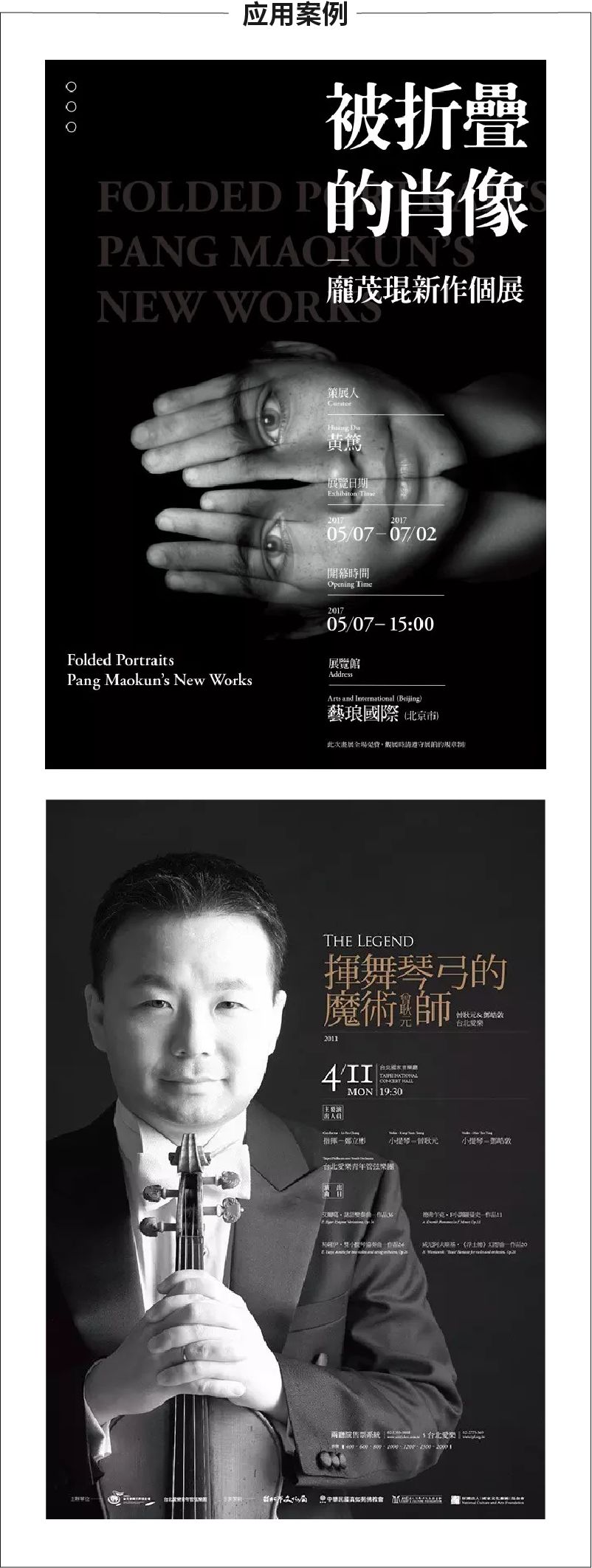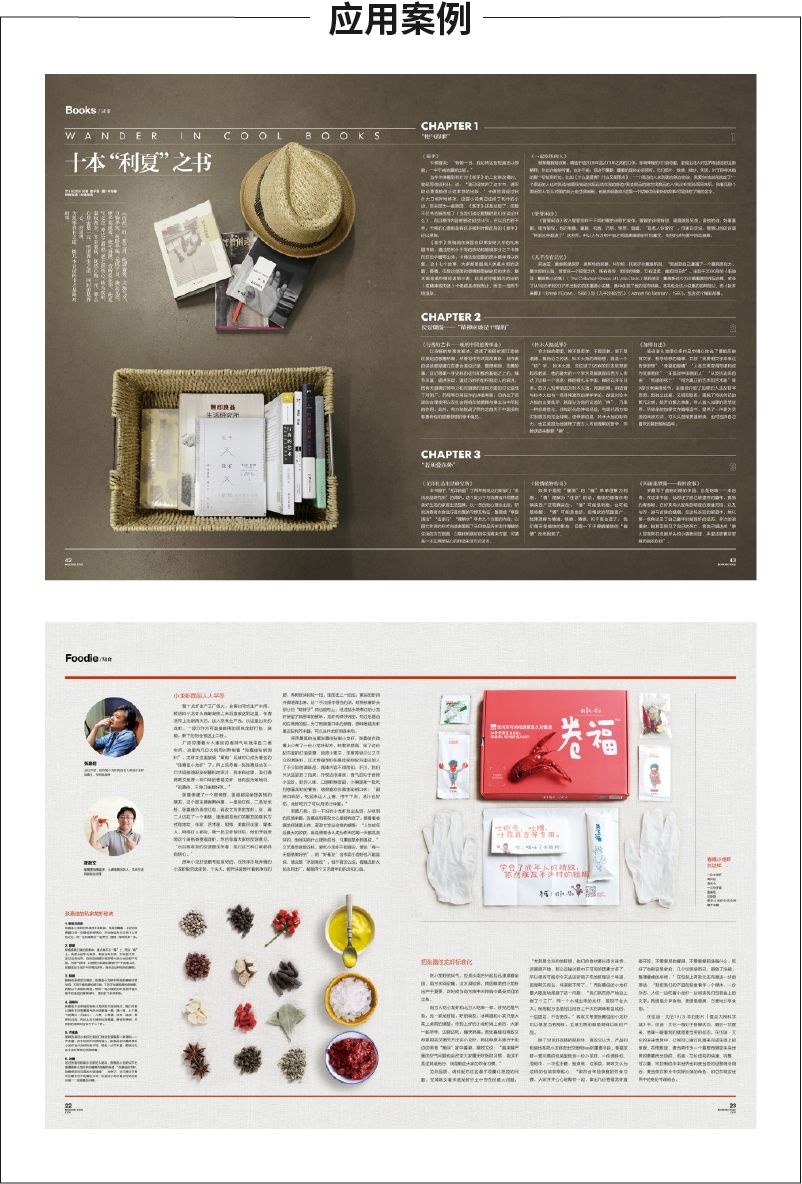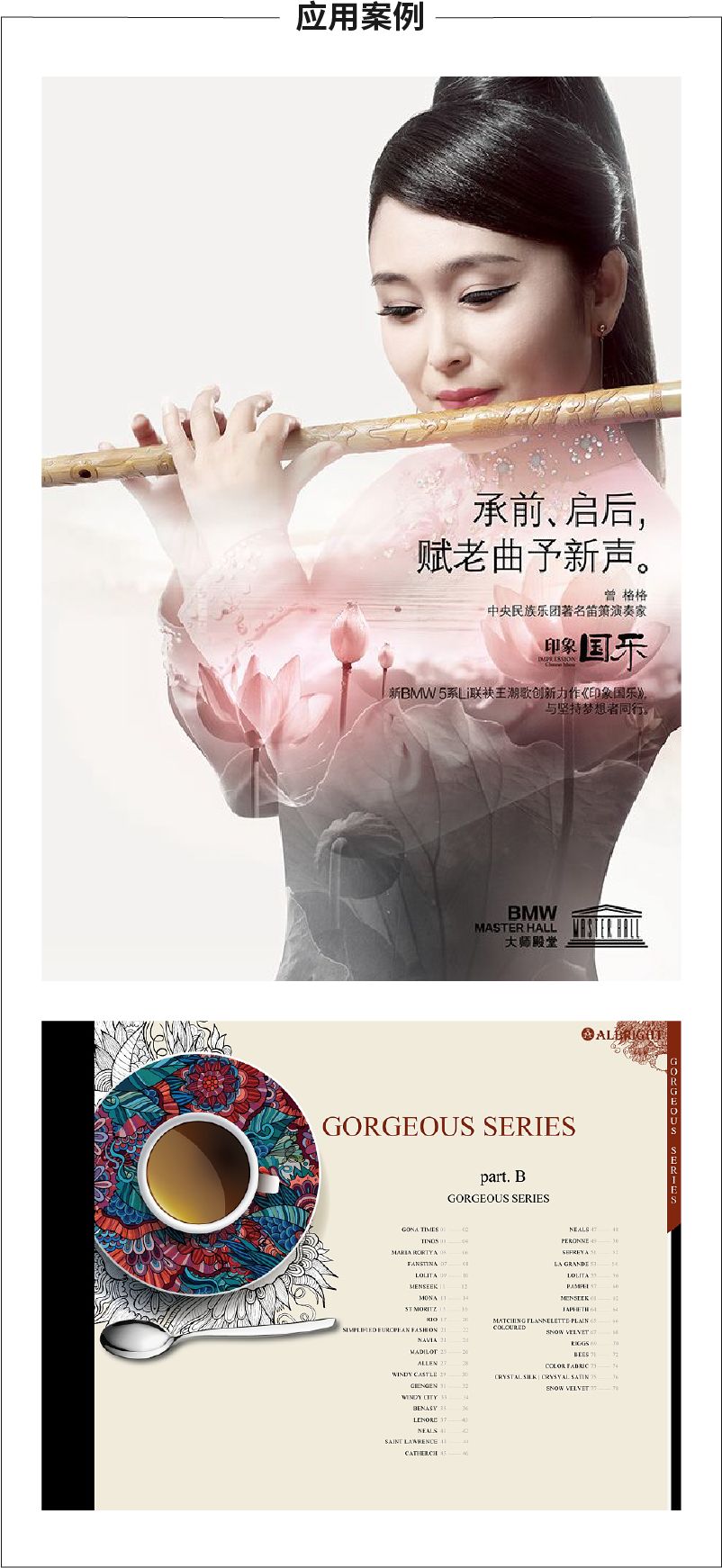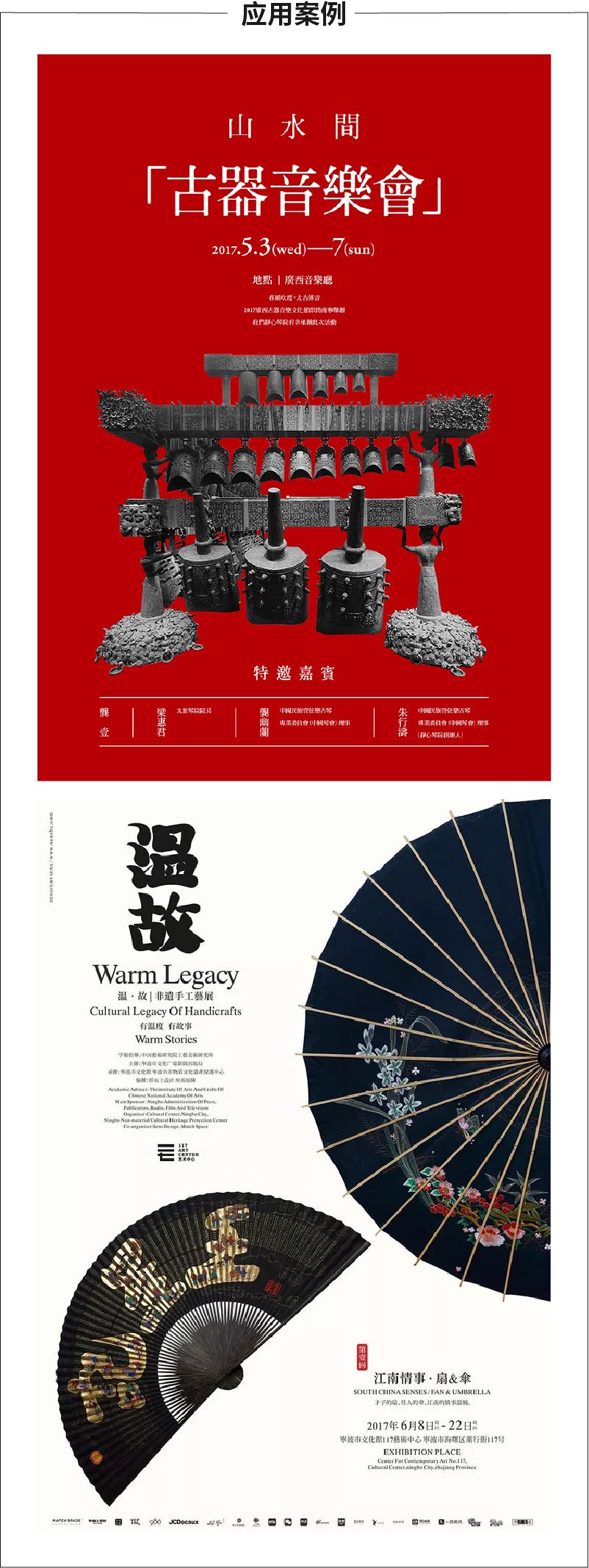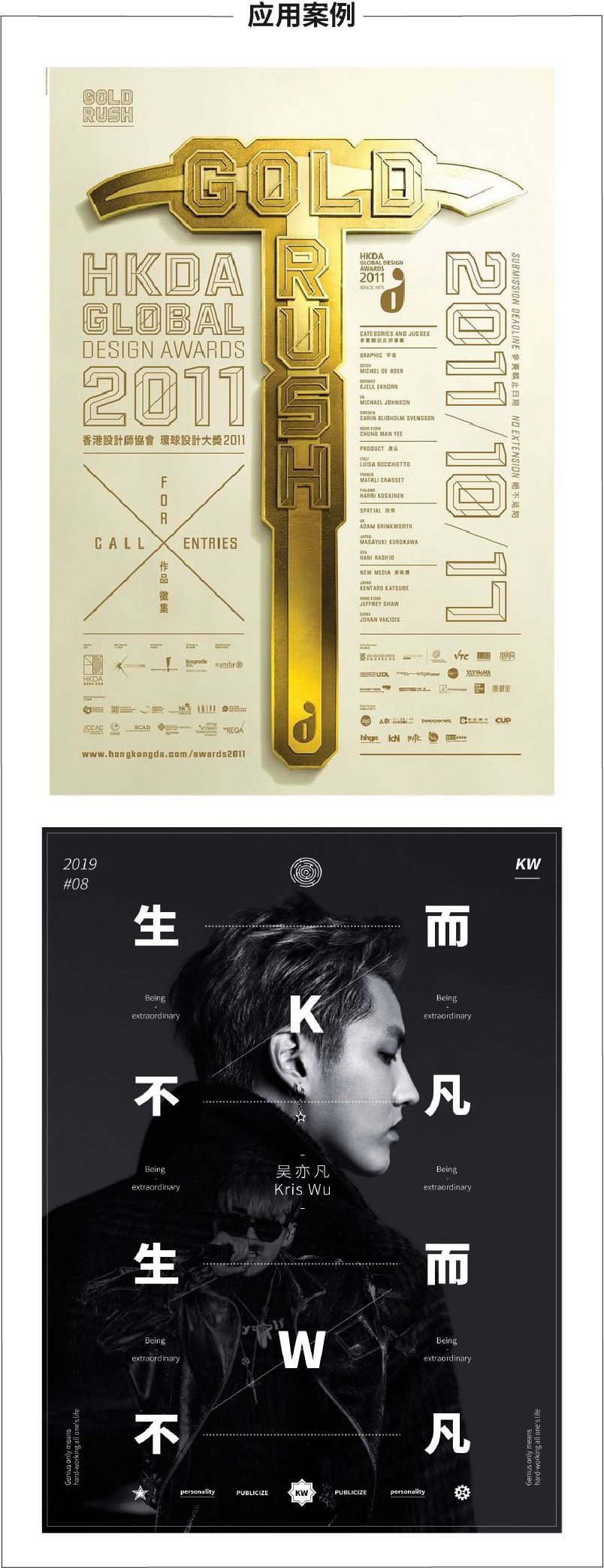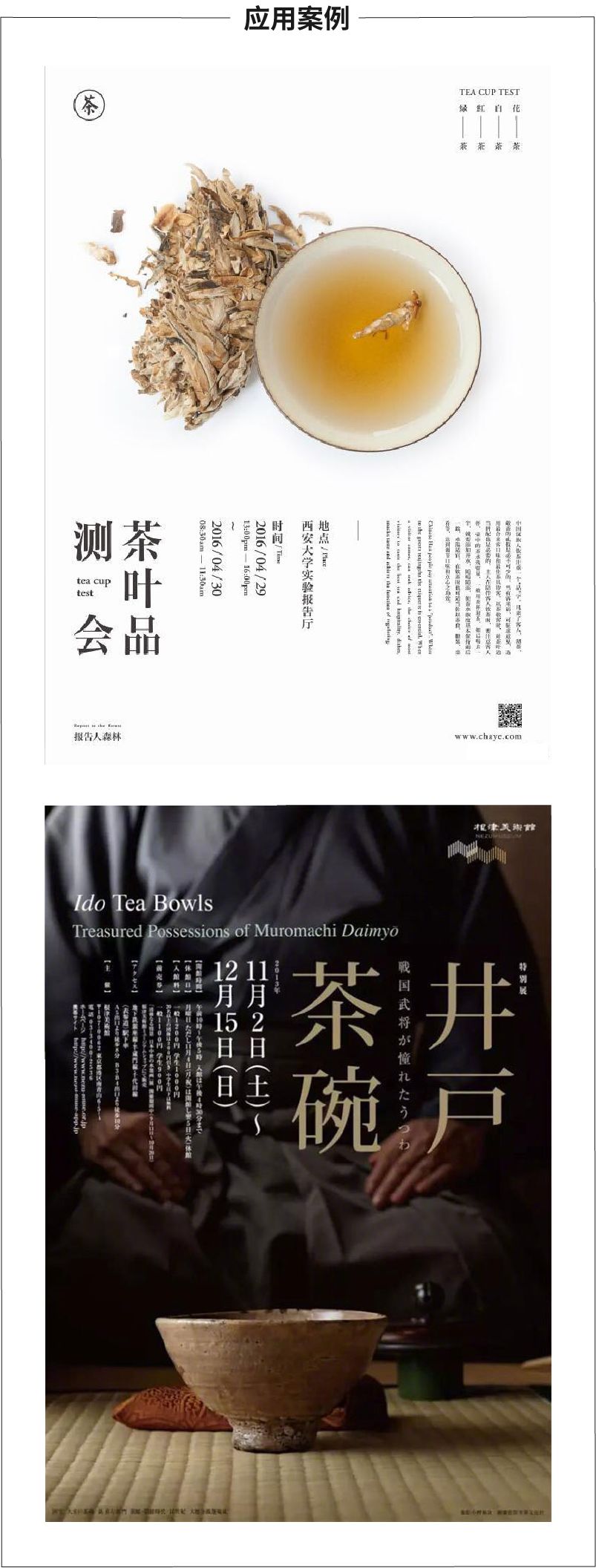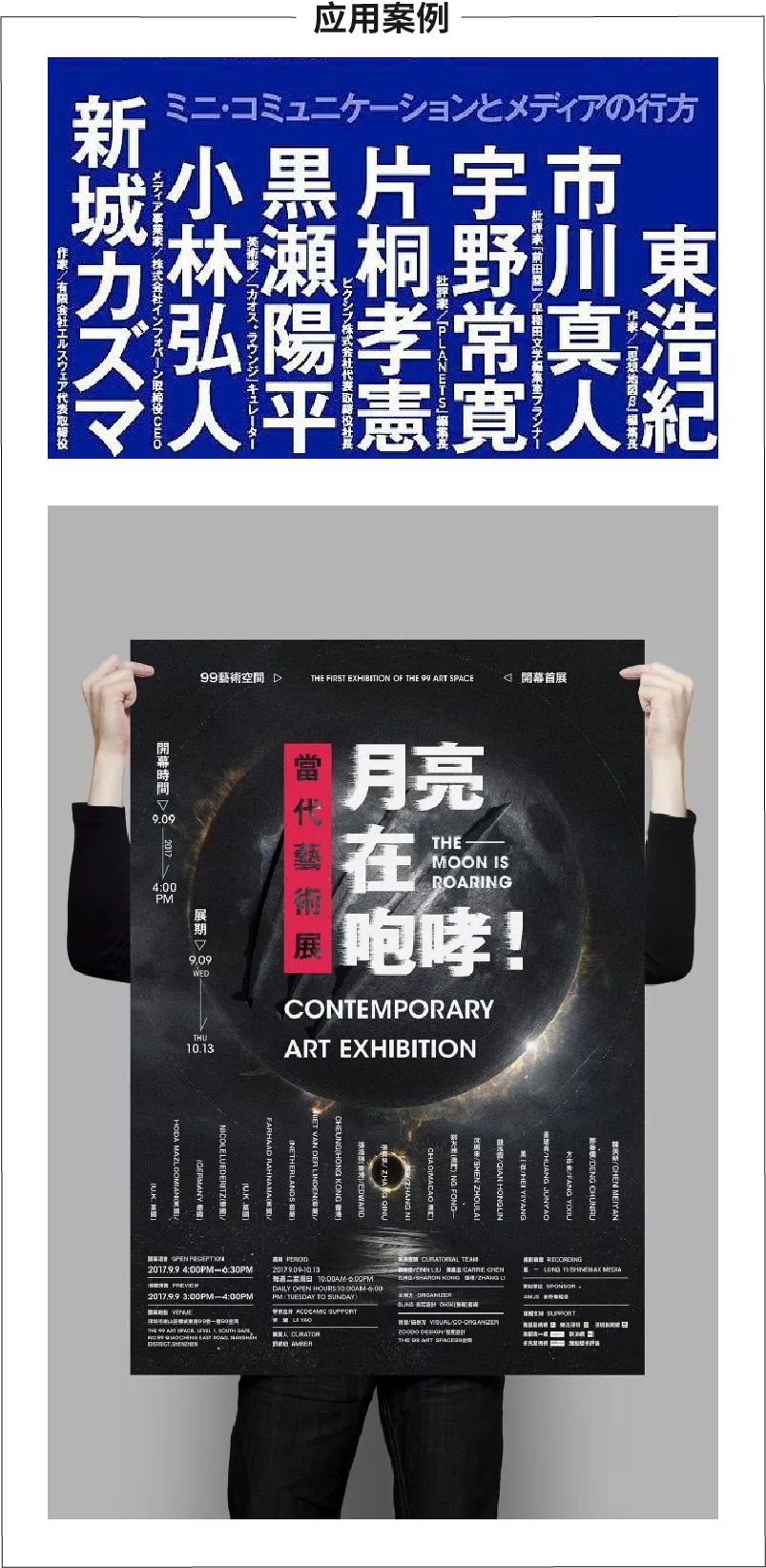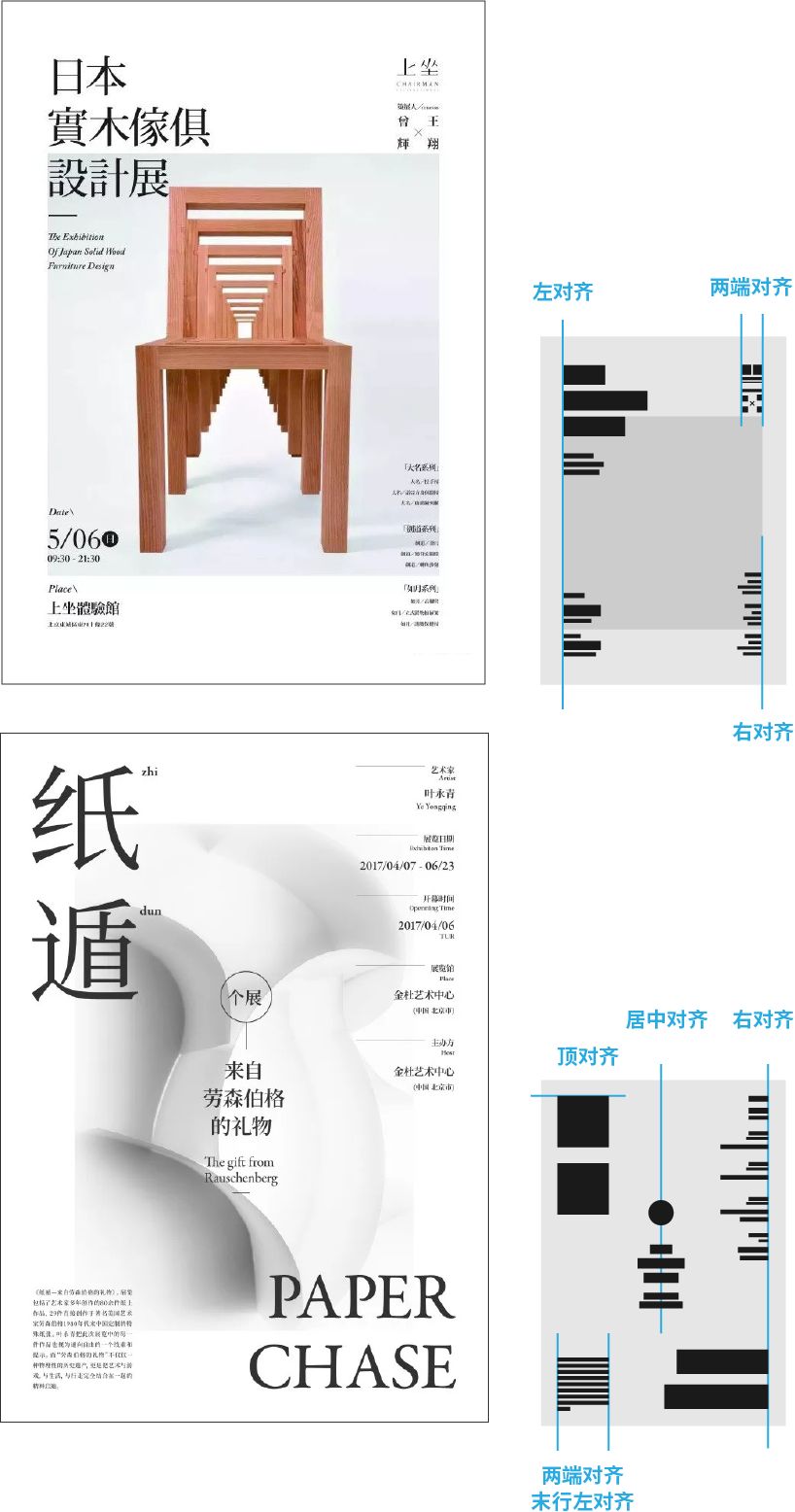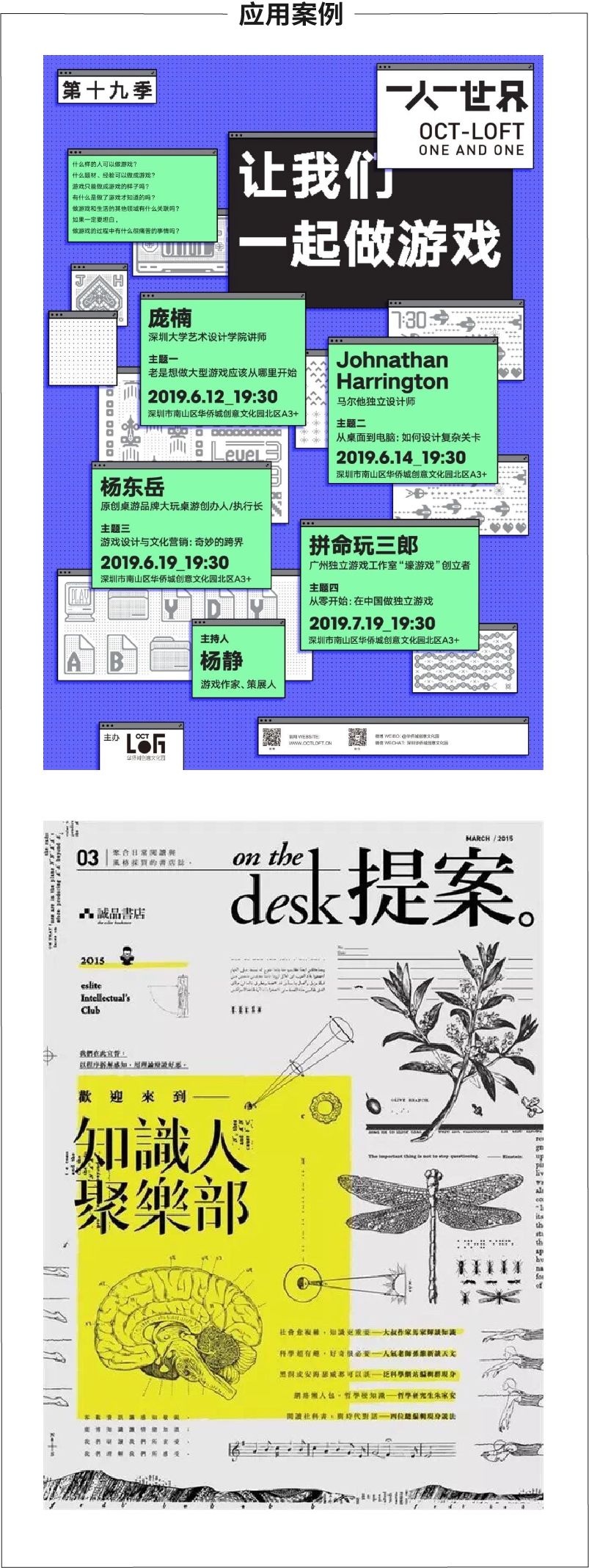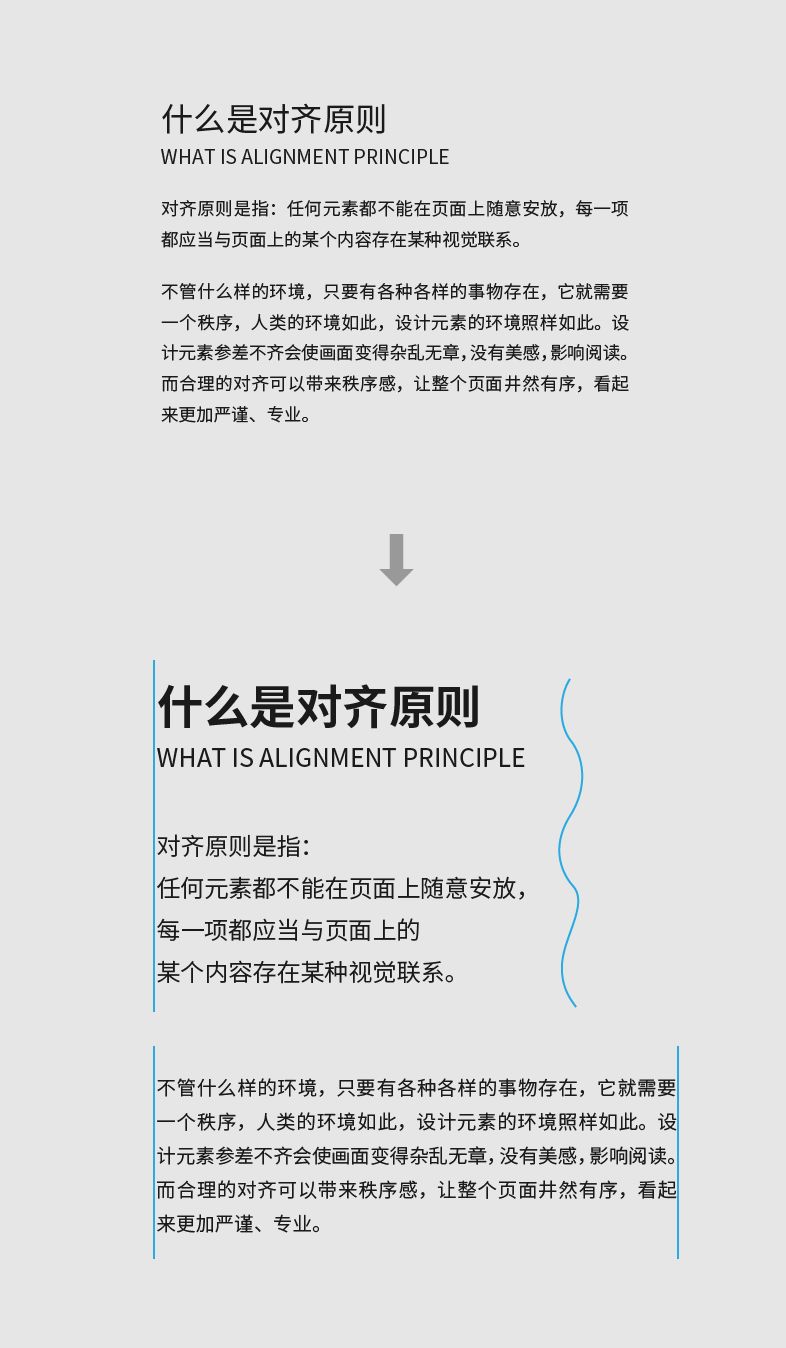
设计总是太乱怎么办?一定是没有做好对齐原则
重复、对比、对齐以及亲密性是版式设计中的四大原则,各种排版形式与规则都是基于这四大原则衍生而来,而掌握这些具有指导性的设计原则,能够帮助我们在短时间内,更快更好的达成设计目标。本期给大家讲解四大原则之——对齐原则。
对齐原则是指:“任何元素都不能在页面上随意安放,每一项都应当与页面上的某个内容存在某种视觉联系”。
在四大原则中,对齐应当是最容易理解的了,因为在我们的生活中对齐几乎就是无处不在。
不管什么样的环境,只要有各种各样的事物存在,它就需要一个秩序,人类的环境如此,设计元素的环境照样如此。左下图设计元素参差不齐,画面显得杂乱无章,没有美感,影响阅读;而右下图运用合理的对齐可以带来秩序感,看起来更加严谨、专业,信息传达效果更好。
为什么要对齐?不仅仅是对用户视觉浏览习惯的考量,还是对页面中信息组织的考量。一方面利用对齐,符合用户的视觉惯性,降低用户阅读负担;另一方面利用不同的对齐形式,能有效组织信息,让页面规整有序、严谨美观。
文字编排常用的对齐方式有:左对齐、两端对齐末行左对齐、右对齐、居中对齐、两端对齐、顶对齐和底对齐等。在进行设计时要根据构图形式选择合理的对齐方式,每种对齐形式所传达的视觉感受也不一样。(对齐名称只是为了便于讲解和记忆,不一定与软件中的名称一致)
左对齐
由于我们的阅读顺序大多是从左往右,所以左对齐是阅读效率最高的对齐方式,也成为了排版中最常见的一种对齐方式。
左对齐的缺点是容易造成右端留白过多,整体视觉失衡。但是这种对齐方式不破坏文字本身的起伏和韵律,能保证较好的阅读体验。还可以避免英文因单词所包含的字符数量不等而不便于左右对齐的编排难题。
两端对齐末行左对齐
在进行大段的文字编排时,常会遇到这样的情况,无论你怎么拉动文本框,文字的两端都无法对齐。
这时可以强制左右两端都对齐,最后一行靠左对齐。这是最常用的段落性文字编排形式,多运用于杂志、画册、报纸等多文字信息内容的编排。使段落文字严谨工整,让版面清晰有序而有条理,提高阅读效率。
居中对齐
多用于居中对称式的版面,给人庄重、肃穆、经典的感觉。因为大段的居中对齐文字会造成分行和阅读困难的问题,所以常用在标题、导语和短篇文字编排中。
右对齐
右对齐的编排方式与人的视线移动方向相反,而且每一行起始部分的不规则增加消耗了阅读的时间和精力,这种格式只适用于少量的文字。
右对齐使用的频率不太高,往往会与图形、照片建立某种视觉联系,获得排版上的平衡。使用右对齐会给人一种人为干预的感觉,因此这种对齐方式会显得比较个性。
两端对齐
两端对齐是指将文字通过调整间距的方式使得两端完全对齐,强制处理成四方形,这样可以达成工整严谨的效果。
顶对齐
顶对齐是纵向排版才会用到的对齐方式,起源于古代的书简,因此采用纵向排版虽然不利于阅读,但是可以营造出复古的文化氛围,有着浓浓的中国味。
底对齐
底对齐也使用在纵向排版,每一行起始部分的不规则增加消耗了阅读的时间和精力,是最不适合阅读的对齐方式,一般只用于少量文字或作为装饰性元素使用。
非横向和纵向对齐
排版不一定只有横向和纵向的视觉方向,也会有其他的方式,在这些视觉方向上,也要通过对齐的原则来规整设计元素。
倾斜对齐
分散对齐
在设计时常会根据构图和空间分割使用多种对齐方式的编排组合,如下图版面中每个信息群组使用的对齐方式也不一样,可以让信息层级更清晰,信息传达效果更好。
自由对齐
打破秩序,没有明确的对齐线,是崇尚随兴,自由活泼,具有诗意、感性的排列方式,为版面设计提供无限的可能性。
为了让大家加深对亲密性原则的理解,提取本期文章的主要内容做为原始资料,运用对齐原则进行设计示范。
按照上一期亲密性原则总结出来的规律,把版面中的文字信息进行分组,使它们各自成为一个视觉单元,建立起条理性和组织性。并按照“字间距< 行间距< 段间距< 组间距”的规则进行亲密性设置,保证各个间距组合之间的相对性比例。
把“标题”、“对齐原则简介”、“对齐方式”,
三组信息分别进行对齐设置
“标题”按照两端对齐的形式,调整文字间距使得两端完全对齐,强制处理成四方形,这样可以达成工整严谨的效果。并把字体改为思源宋体,与正文的思源黑体增加字体对比:
“对齐原则简介”文字采用左对齐格式,可以保持文字本身的起伏和韵律,还能保证较好的阅读体验。另外文字较多的一段,可以采取两端对齐末行左对齐格式。使段落文字严谨工整,让版面清晰有序而有条理,提高阅读效率。
“对齐方式”信息组使用右对齐形式,增加对齐方式的多样性。虽然每一行起始部分的不规则增加消耗了阅读的时间和精力,但是也增加了排版的节奏感。
把设置好的文字信息放置到版面中,并使用网格进行规范和辅助对齐,使用网格可以快速分割版面以及找准对齐关系,辅助我们的设计更严谨。
沿用上期使用的孟菲斯风格元素丰富画面。给各个信息组加入伪立体效果的外框,让信息分割更明确,加入外框后画面也要遵循对齐原则。
加入小圆点当做背景机理,并增加各种几何形状来丰富画面。增加活泼感和趣味性。方案一设计完成:
尝试使用其他对齐方式和构图形式设计另一个方案:
加入孟菲斯风格元素丰富画面,遵循对齐原则进行排版,方案二设计完成:
总 结
视觉规范最基础的要求就是:整齐、规范、有条理。大多数情况下,设计做的不美观,很大的原因就是在排版方面过于随意,尤其是很难或者没有意识做到对齐。
无论版面的信息多少、位置如何变化,只要遵循对齐原则,保证元素间的对齐关系,就能够使版面统一、简洁、更有条理,还可以引导视觉流向,有助于信息更好传达,当然也更美观。在进行设计时必须先掌握最基本的程序化的美,才可以升华到最“随意”的原始美。